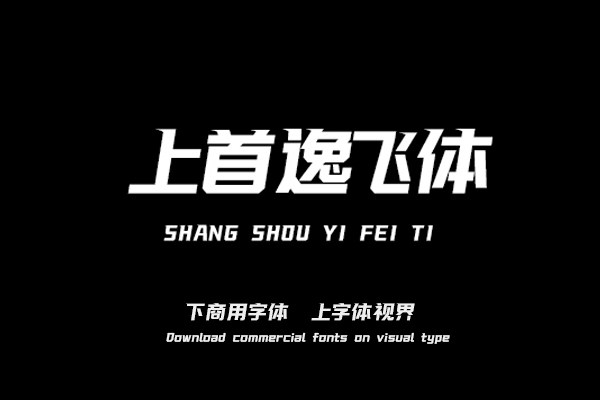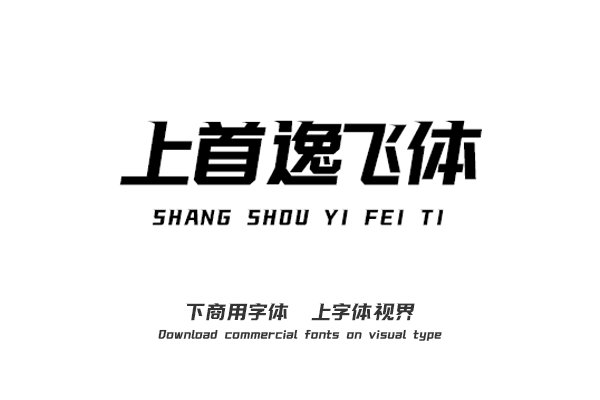
上首逸飞体,简体中文约6763字,字体笔画横细竖粗,横竖笔划增加了突出的尖角,整体字形为斜体,具有飘逸的风格,给人一种飞驰的感觉。适用于搭配标志、广告标语、商业......购买须知:“下载服务费”与“字体VIP”所获得字体 仅用于个人非商用, 商用请联系付费授权。本字体为电脑用字,手机没有root权限不支持直接手机换字(手机如何root,请自行百度搜索教程)。购买前请先 了解清楚后再付款 ,字体为虚拟产品无法回收 一旦购买不支持退款。